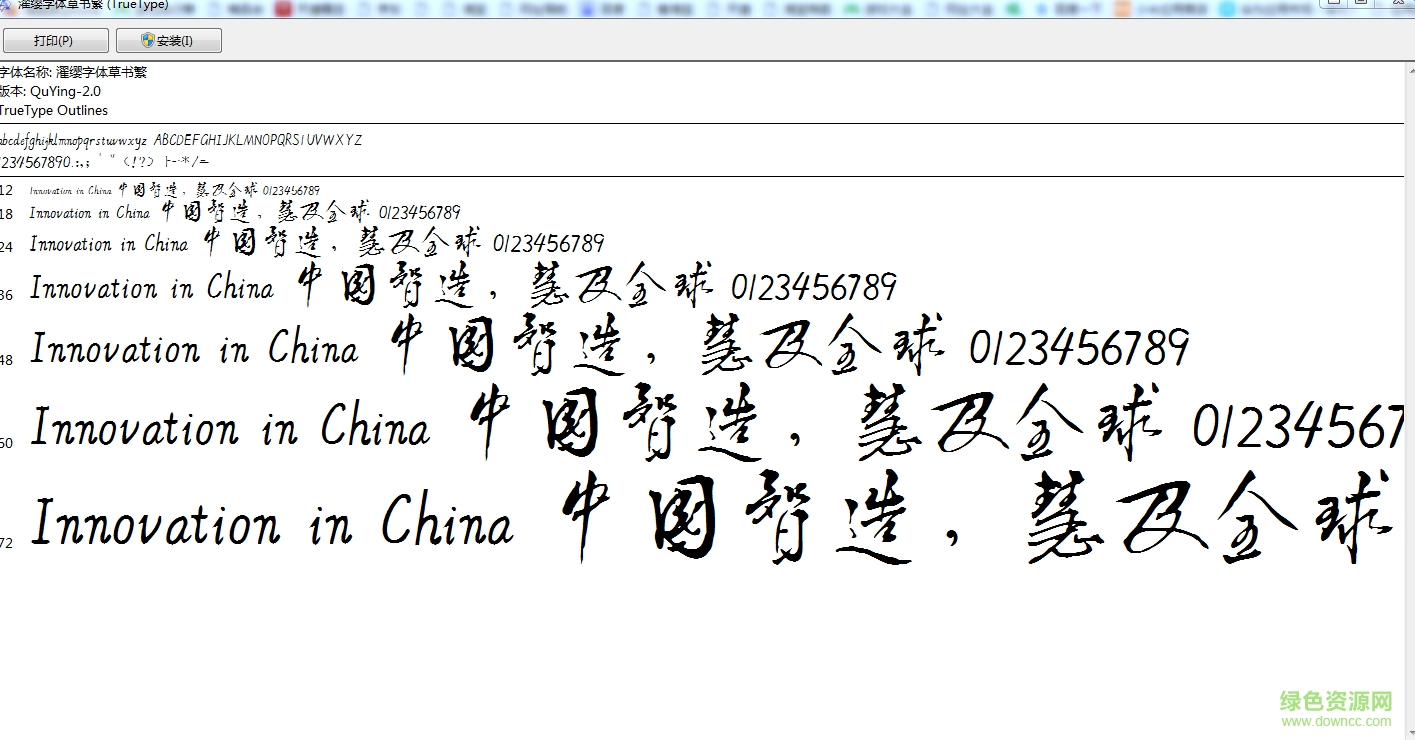
濯纓字體草書繁體是一款極具藝術(shù)價值的草書字體,用筆恣肆,縱逸奔放,瀟灑又典雅,喜歡這款字體的朋友歡迎在綠色資源網(wǎng)下載收藏!
濯纓字體草書繁是一款應(yīng)用于設(shè)計方面的的中文草書字體,該字體筆鋒犀利,威武有形,整體效果非常的出眾,可適用于牌扁設(shè)計、廣告設(shè)計、平面設(shè)計、印刷包裝等領(lǐng)域,有喜歡的朋友快下載收藏吧。